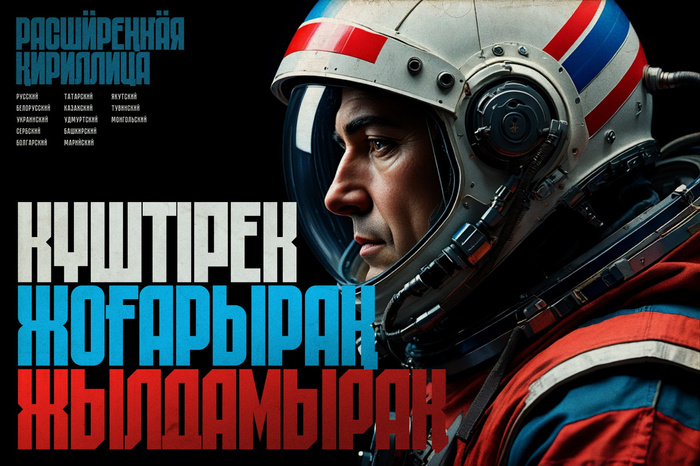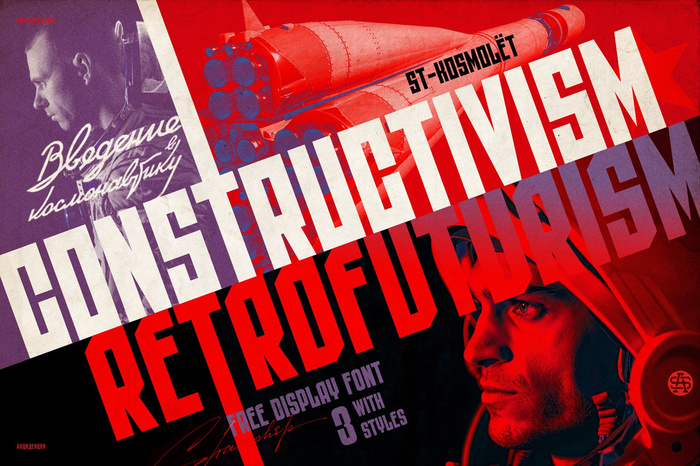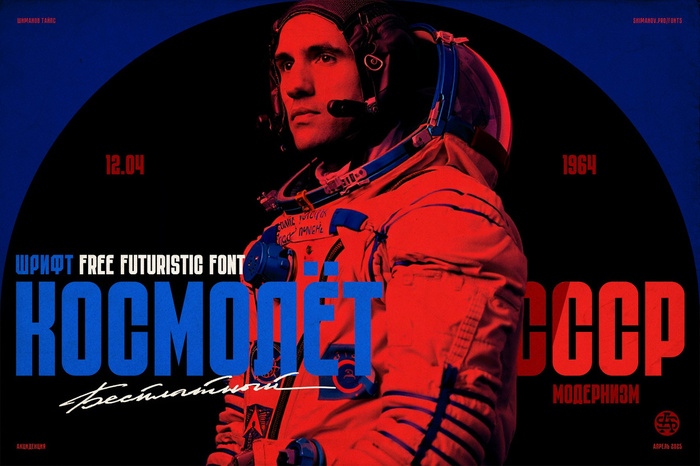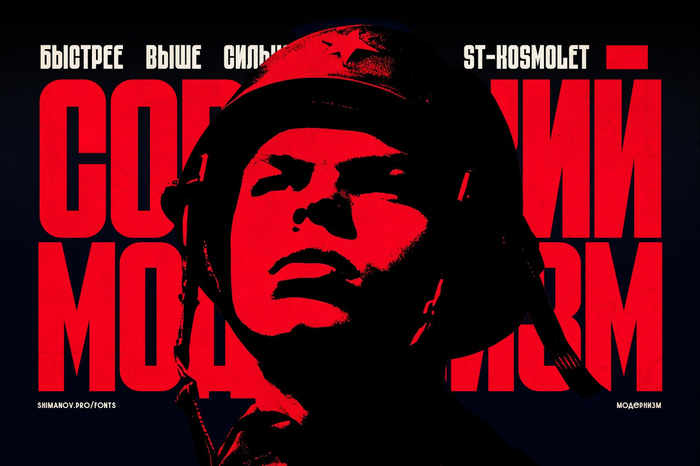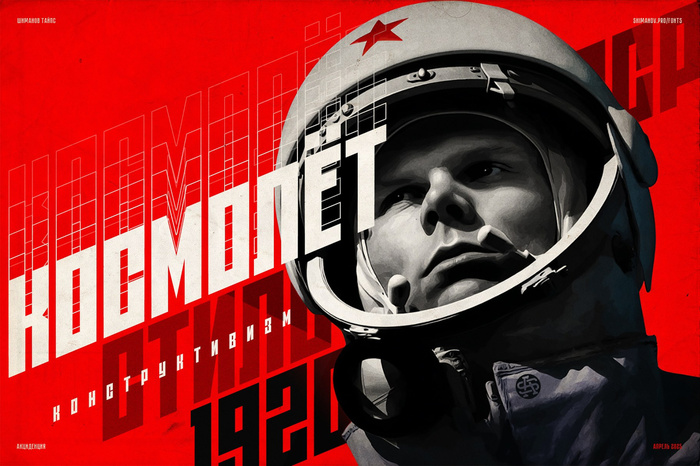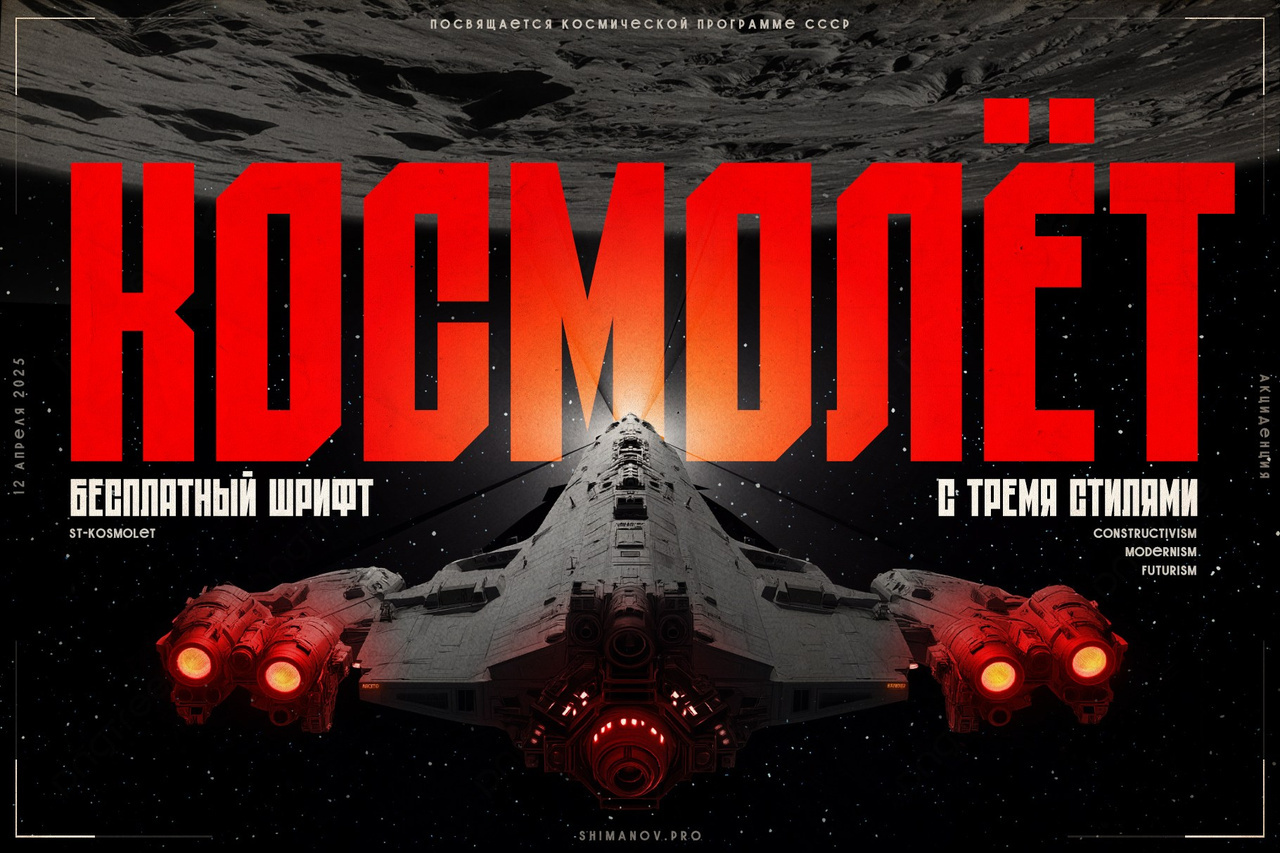
Шрифт Космолёт
Космолёт. Поздновато увидел) Нужно было вчера. Понравился и сам шрифт и презентация (сохраняю оригинал)От автора: Шрифт СТ-Космолёт — это посвящение космической программе СССР, эпохе научного романтизма и технического прогресса.Автор: Александр "STAN" Шиманов